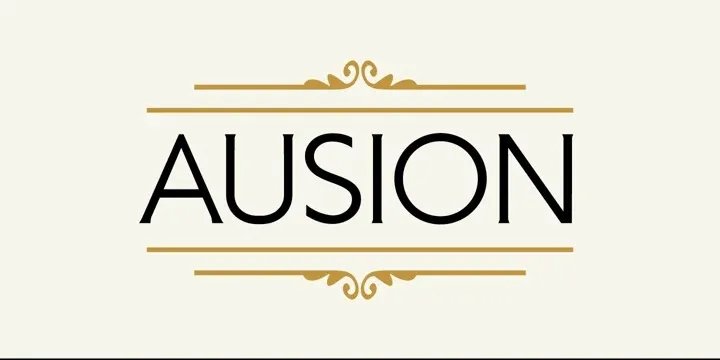
A Ausion Font é uma elegante serif, perfeitamente adaptada para projetos modernos e estilizados. Feita por designers versáteis do Andfonts, esta font oferece um estilo refinado que se destaca de maneira notável, tornando qualquer projeto mais chamativo e criativo. Seu caráter sofisticado combina bem com diversos tipos de ideias gráficas, tornando-a uma escolha ideal para quem busca um toque diferenciado em seus projetos. Com sua versatilidade impressionante, a Ausion Font é uma escolha perfeita para designers que desejam dar seu trabalho uma aparência ainda mais profissional e sofisticada. Com ela na sua coleção, não hesite em explorar novas maneiras de expressar suas ideias criativas.